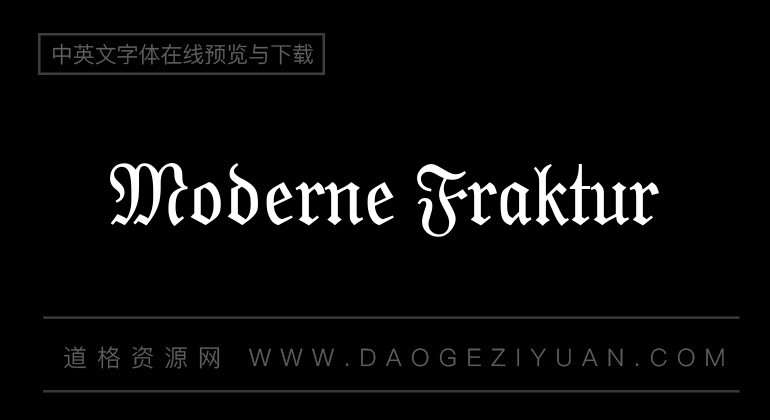
Moderne Fraktur
Moderne Fraktur 字体是一种经典的德国文艺复兴风格的衬线字体,它由著名的德国字体设计师Friedrich Wilhelm Kleukens于1917年设计。它的特点是字母的曲线细腻,笔画的连续性好,具有明显的衬线特征,而且整体气质非常舒缓,即使在大小变化时也不会失去细节。它可以用于传统的书法,也可以用于报纸、杂志、电子书籍等印刷品的设计上。
Moderne Fraktur是一款非常不错的手写艺术字体,具有很好的视觉感,适合于文化类的宣传设计、商业类品牌的广告和产品包装设计以及个性化文字排版等较多场景。